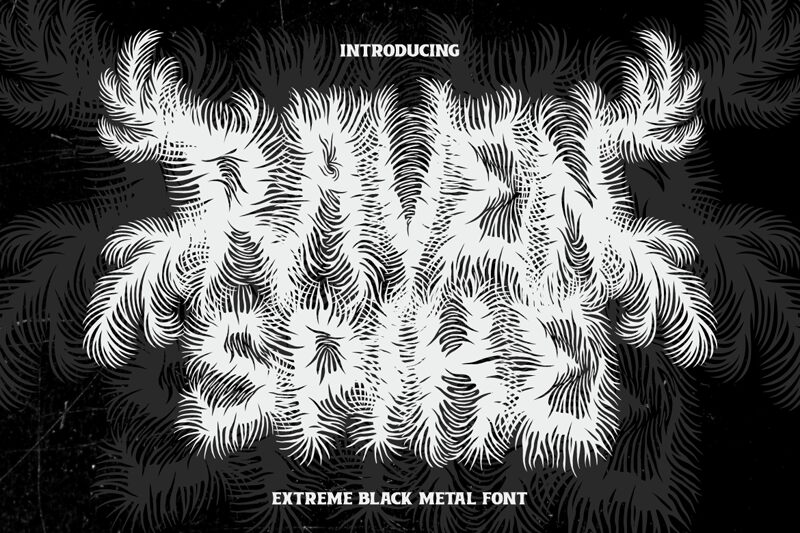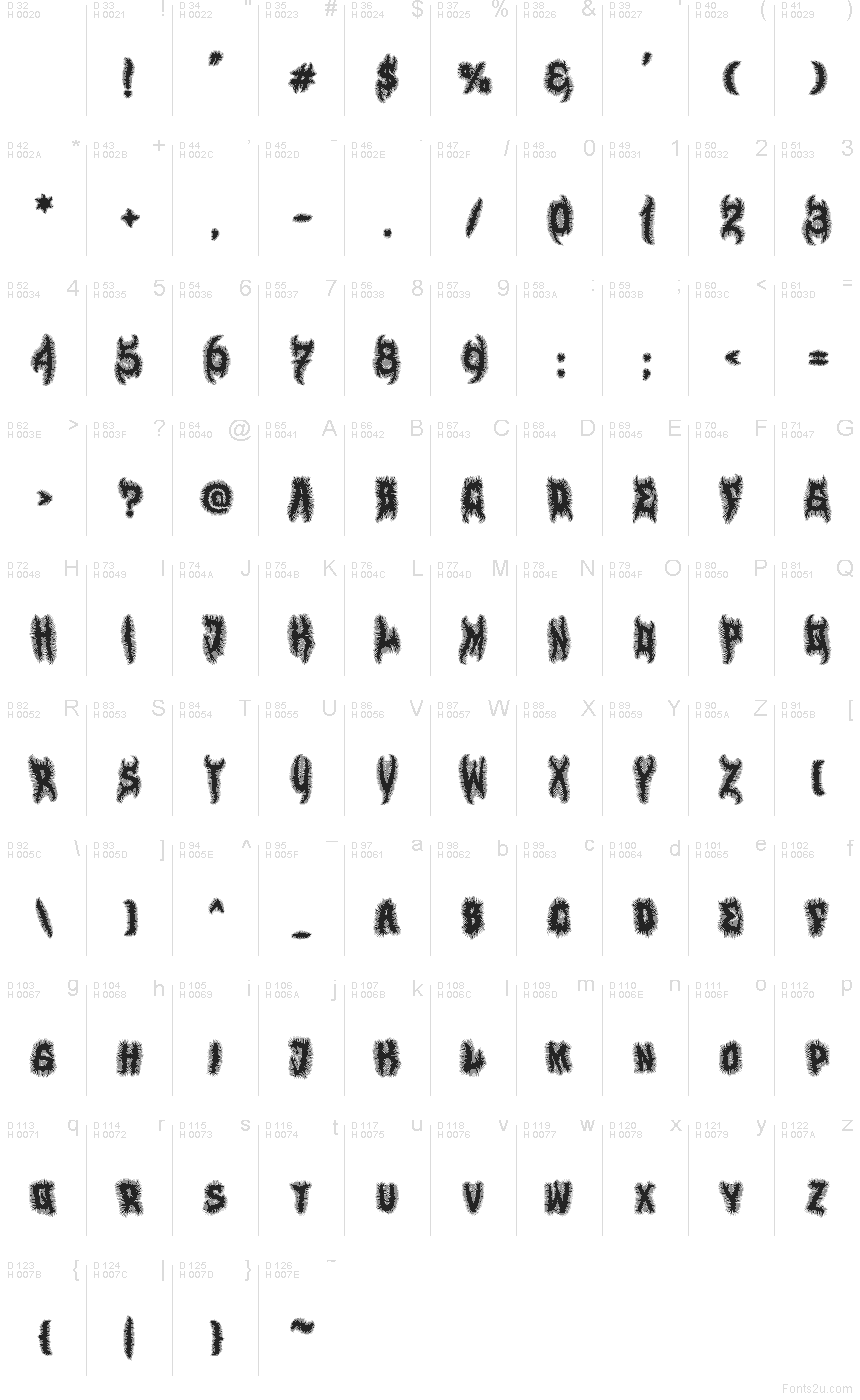
Raven Spike di Shanaf Studio è un font horror gotico gratuito, caratterizzato da lettere che sembrano invase dalla vegetazione, piumose e quasi selvagge. Le maiuscole sembrano strappate ai flyer di black metal e all'estetica dark fantasy, con bordi densi e spinosi che trasformano ogni carattere in una silhouette irta, piuttosto che in un blocco di testo pulito.
Questo font gratuito del 2025 è ideale per copertine di album, titoli di locandine, branding di videogiochi, testate di fanzine e grafiche per eventi in cui il lettering deve fungere tanto da texture quanto da testo. Si presta bene anche per brevi titoli, card di presentazione e monogrammi, poiché i bordi frastagliati conferiscono anche a poche lettere una presenza carica e sinistra.